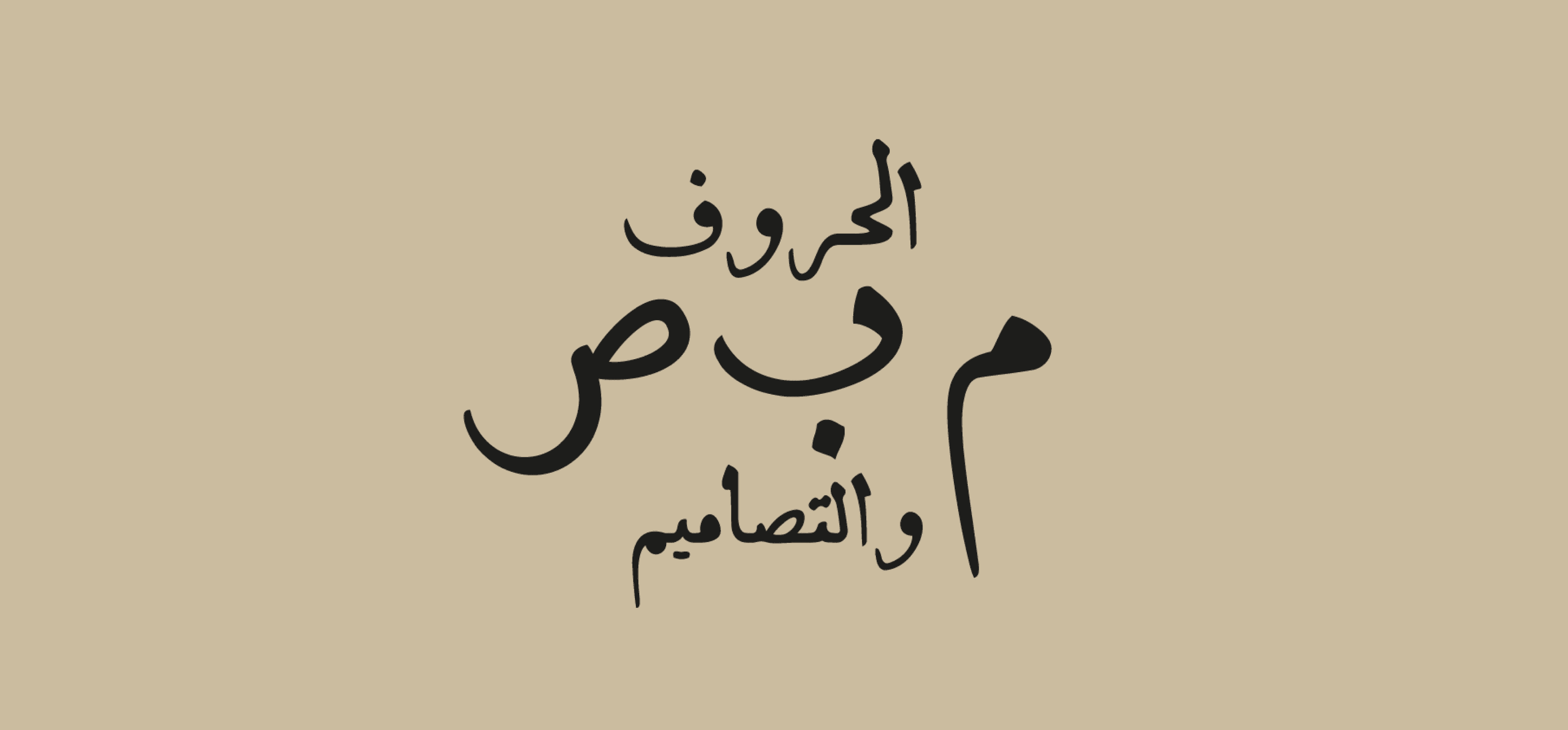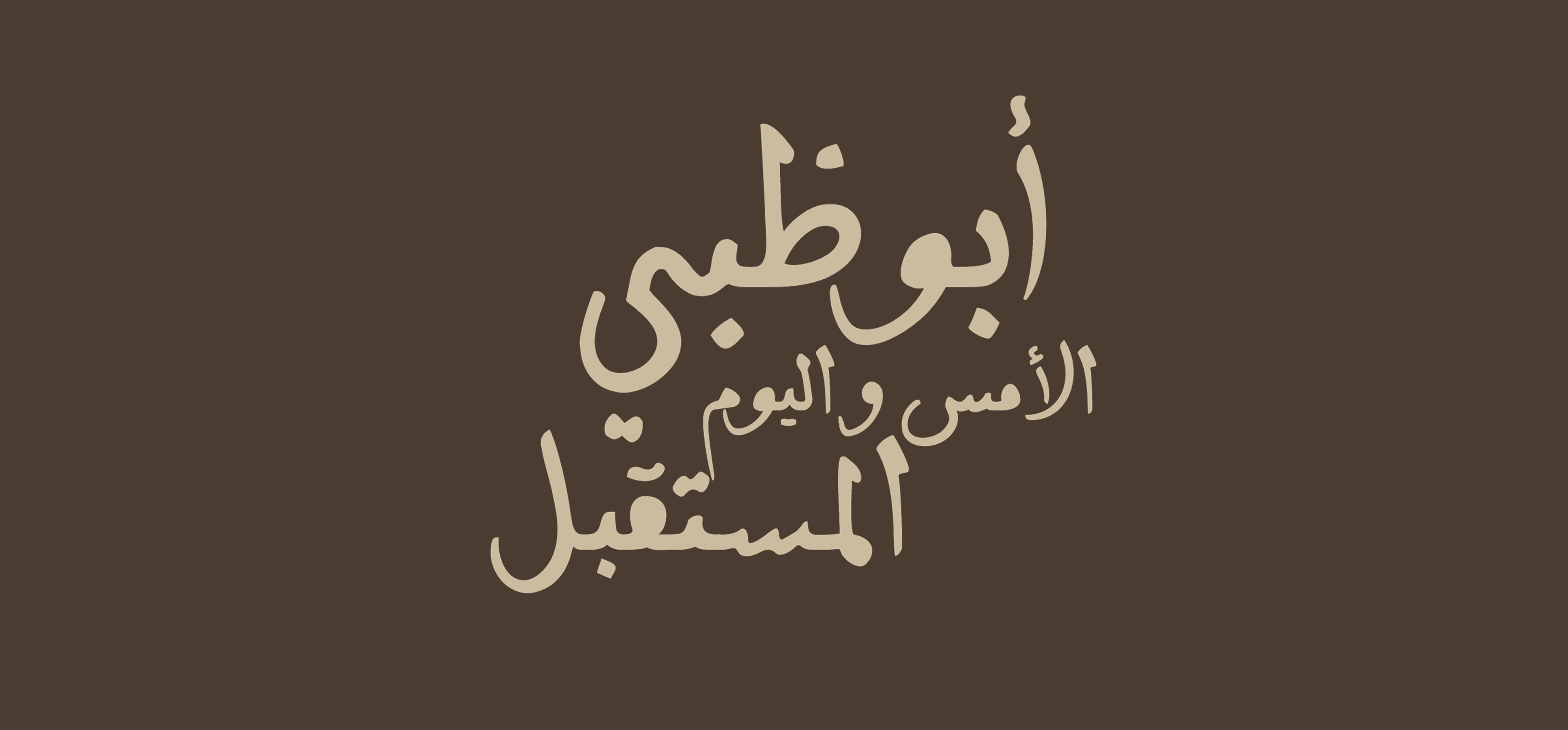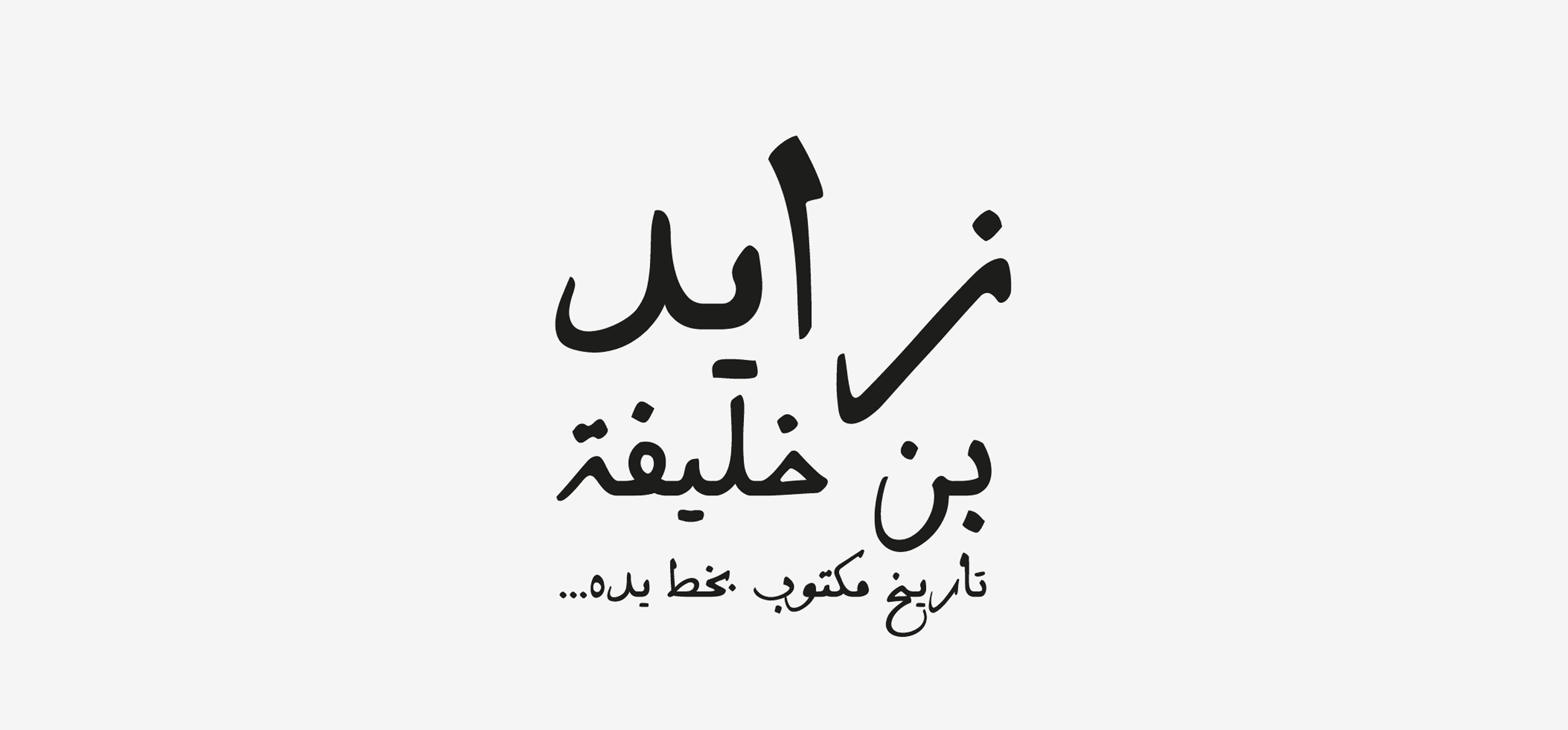
تم تصميم هذا الخط العربي المخصص حصريًا لحكومة أبوظبي في دولة الإمارات العربية المتحدة. وقد جاء استجابة لطلب فريد من نوعه لإنشاء خط رقمي مستند إلى خط اليد الخاص بالشيخ زايد بن خليفة آل نهيان (1840–1909).
بدأت عملية التصميم بالحصول على خطابات ومواد تاريخية أصلية مكتوبة بخط يد الشيخ زايد، أول رئيس لدولة الإمارات العربية المتحدة. تم دراسة هذه المواد بعناية، واعتمد عليها في تصميم الخط بهدف التقاط الروح الأصيلة لخط اليد وأدوات الكتابة المستخدمة في ذلك الزمن.
وكان التحدي الأكبر هو توحيد الخط بأسلوب بصري متماسك، نظرًا لتفاوت التفاصيل وخصائص الكتابة في المواد الأصلية المقدمة.